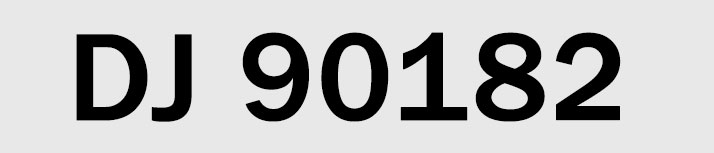
Problematiske bilskilt
Ved begynnelsen av 2002 dukket det opp en ny type bilnummerskilt. Den velkjente nummerskilt-skriften som hadde vært i bruk siden 1971, ble gradvis avløst av en ny, som estetisk sto langt tilbake for den gamle. Den nye skriften hadde også dårligere leselighet. Dette førte til praktiske problemer ved avlesing av bilder av nummerskiltene, tatt fra fotobokser o.l.
Problemene har ført til en fullstendig snuoperasjon hos Vegdirektoratet. Status pr. juni 2003 er at det vil bli innført en helt ny, og tredje skilttype i Norge. Denne mener man skal korrigere de problemene man har hatt med skilttypen som ble innført i 2002.
Historien om de norske bilskiltene er en interessant anskueliggjøring av skrifters estetikk og funksjon, og om verdien av typografisk kompetanse når slike avgjørelser skal tas.
Lik skiltbredde
Årsaken til at man forlot den opprinnelige skilttypen, var først og fremst at man ønsket skilt av lik bredde: hittil har dette visstnok ikke vært tilfelle. De tall og bokstaver som har vært brukt på de gamle skiltene har hatt ulik bredde, noe som også har gitt ulik bredde på skiltene. Især 1-tallet på den tidligere skilttypen er svært smalt. Det betyr at hvis det er ett eller flere 1-tall i nummeret, blir det smalere enn numre uten 1-tall.
At 1-tallet har lite «kjøtt» (luft) på sidene, gir på den annen side svært pene tallsammensetninger - innen typografien blir det omtalt som god utlikning av tallene. Hvis 1-tallet skulle hatt like stor bredde som de andre tallene, i den formen det inntil nå har hatt, ville det blitt svært mye luft på sidene av det.
En annen konsekvens av de ulike breddene på tall og bokstaver, ifølge Vegdirektoratet, er at W og M ikke har vært benyttet i det hele tatt. Dette fordi de er så mye bredere enn de andre bokstavene.
For å oppnå lik bredde på skiltene, valgte man å gjøre bredden på alle bokstaver og tegn like. Men den videre historien viser at dette ikke var en nødvendighet.
Med den standardiserte bredden på tall og bokstaver, kunne alle bokstavene brukes (de skandinaviske bokstavene Æ, Ø og Å forutsetter jeg ikke benyttes). Denne standardiseringen av tegnbreddene (alle er nå 4,9 cm brede) betyr reduserte produksjonskostnader. På de gamle skiltene varierer tallbredden fra 2,27 cm til 5,57 cm.
Blant andre årsaker til de nye skiltene, er nevnt at de er tynnere og derfor mer økonomiske å lage. Årsoblaten har dessuten fått en fast plass. Skiltene er også forberedt for norsk EU-medlemskap (de har plass til en «N» omkranset av EU-symbolet).
Kerning
Med den nye utformingen av 1-tallet, der utløperen øverst er vesentlig lengre og seriffen (tverrstreken) nederst er svært bred, har man oppnådd at alle tallsammensetninger ser tilfredsstillende ut, selv når alle tallene er like brede. Dette er et grep som man kjenner også fra endel typografiske skrifter, der lik bredde på tallene har stor praktisk betydning ved tabellsats, og der det er en fordel at tallsammensetninger ser tilfredsstillende ut uten at det må «kernes» (avstandene til nabotegn må reduseres) når 1-tallet står sammen med andre tall. (Slik «kerning» kan for øvrig automatiseres, og er egentlig ikke noe problem i grafiske programmer.)
For tallenes vedkommende er avgjørelsen om lik bredde grei. Det er mer tvilsomt om dette kan løses tilfredsstillende for bokstavenes del. F.eks. har bokstavene W og I i utgangspunktet svært ulik bredde. Det finnes skrifter som f.eks. Courier som har løst dette, men det er en skrivemaskinskrift for bruk på datamaskiner, og den har ikke typografisk kvalitet. Men foreløpig er mitt eksempeltilfang for dårlig til å kunne konkludere.
Bilskilt av den gamle typen.
Bilskilt av den nye typen.
Ingeniørarbeid
Hvis man underkaster tegnene på de nye skiltene en estetisk vurdering, er inntrykket av de nye skiltene at bokstaver og tall har en kantet, uskjønn utforming. Det er mange rette linjer, - kurvene er blitt redusert i antall og lengde. F.eks. 8-tallet i den gamle skilt-skriften består kun av kurver. Det naturlige pennestrøket for å skrive tallet er til stede. På de nye skiltene ser derimot linjalen ut til å ha vært flittig brukt. 8-tallet har kun korte kurver der de rette linjene møtes.
Skriften på de nye skiltene bærer preg av å være et ingeniørarbeid, der skriftkunnskap og estetikk har vært mangelvare. Jeg har ikke kunnet bringe på det rene om noen personlig vil påta seg ansvaret for utformingen. Vegdirektoratet opplyser at skriften på skiltene ikke er en eksisterende font (skrift), men at den er en egen «norsk konstruksjon», som er gjort av Åstvedt Industrier i Bergen.
De gamle skiltene har en skrift som estetisk holder et høyt nivå. Den har former som vi kjenner igjen fra trykt materiale som omgir oss. Skriften er den samme som brukes på norske veiskilt. Særlig tallene er vakre.
8-tallet i ny og gammel (til høyre) utforming.
Alternativer finnes
Det er forståelig at man ønsket en standardisering av tallbredden, slik at fem sifre kan fylle den samme bredde uansett hvilke tall det gjelder. Det er blitt løst på en akseptabel måte i den nye skriften, ved å gi 1-tallet en bredere form.